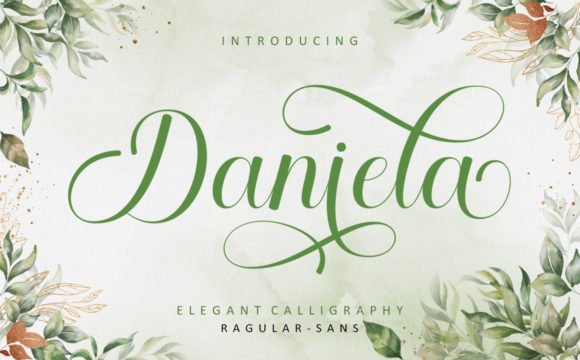
Creativefabrica Daniela Font 2021
[Creativefabrica] Daniela Font (2021)
Daniela - прекрасный и универсальный шрифт в дуэте (шрифт и без засечек).
Он добавит роскошную искру в любой дизайнерский проект, который вы хотите создать!